Danh sách này không chỉ mang đến cho bạn cái nhìn tổng quan về những kiểu chữ thiết kế phá cách, mà còn giới thiệu những xu hướng tiên phong đang định hình tương lai của nghệ thuật typography. Nếu bạn đang tìm kiếm nguồn cảm hứng để nâng tầm thương hiệu, tạo dấu ấn cho sản phẩm truyền thông, hay xây dựng giao diện kỹ thuật số đột phá, bài viết này chính là cánh cửa dẫn lối vào thế giới typography hiện đại, đầy sáng tạo của năm 2025.
Sau khi thưởng thức những kiểu chữ độc đáo và đầy sáng tạo ở phần đầu, chúng ta bước sang phần 2 với danh sách các kiểu chữ không kém phần ấn tượng. Đây không chỉ là tập hợp những thiết kế đặc sắc mà còn là những công cụ mạnh mẽ, mở ra vô vàn khả năng ứng dụng trong các lĩnh vực thiết kế thương hiệu, truyền thông, và sản phẩm kỹ thuật số hiện đại.
Phần tiếp theo sẽ đưa bạn đến những kiểu chữ thể hiện sự pha trộn tinh tế giữa nét đẹp hiện đại và các giá trị cổ điển. Một số kiểu chữ mang phong cách táo bạo, phản ánh xu hướng tiên phong của thời đại số, trong khi số khác lại tái hiện những di sản lịch sử thông qua góc nhìn mới mẻ, đầy sáng tạo. Sự đa dạng này không chỉ làm phong phú thêm bộ sưu tập của bạn mà còn mang lại cơ hội để truyền tải thông điệp với cá tính riêng biệt, giúp các dự án thiết kế thêm phần sống động và đáng nhớ.
Mỗi kiểu chữ trong phần này không chỉ là một sản phẩm thiết kế, mà còn là một câu chuyện đầy cảm hứng, được thể hiện qua từng đường nét và chi tiết. Đây chính là cơ hội để bạn khám phá những lựa chọn typography có khả năng định hình phong cách và nâng tầm ý tưởng sáng tạo của mình. Hãy cùng Arena Multimedia tiếp tục hành trình tìm kiếm những kiểu chữ hoàn hảo, đồng hành cùng bạn trong việc tạo nên những thiết kế đột phá.
16. Font chữ: Cina Sans (Andrés Torresi)
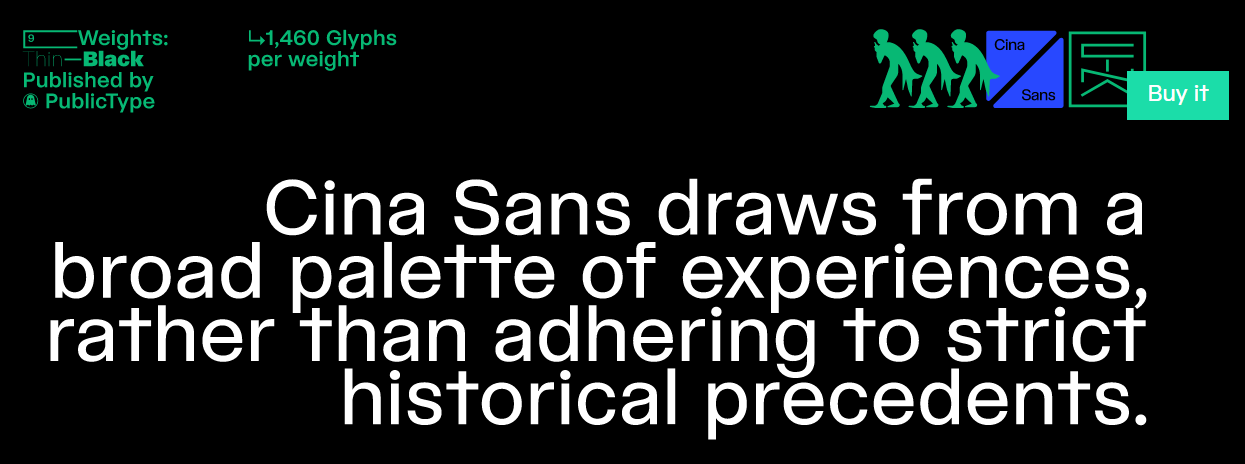
Cina Sans là kiểu chữ sans serif đậm cá tính, thuộc dòng Neo-Grotesque. Kiểu chữ này lấy cảm hứng từ Helvetica – một biểu tượng trong lịch sử thiết kế chữ nhưng được tái hiện qua nhiều lần cải tiến để tạo nên diện mạo mới, hiện đại và độc đáo hơn. Cina Sans là kết quả của sự nghiên cứu và tâm huyết của nhà thiết kế Andrés Torres, người luôn trăn trở với việc kế thừa và phát triển di sản lịch sử của các kiểu chữ kinh điển.
Bộ sưu tập Cina Sans bao gồm 9 độ đậm (weight), mỗi độ sở hữu 1.460 ký tự, mang đến sự đa dạng và linh hoạt vượt trội. Với thiết kế nhấn mạnh vào tính ứng dụng mà không hy sinh thẩm mỹ, Cina Sans không chỉ là một kiểu chữ mà còn là một công cụ thiết kế mạnh mẽ, giúp các nhà sáng tạo truyền tải thông điệp một cách hiệu quả và ấn tượng.
17. Font chữ: Vitamiin (Typokompanii)
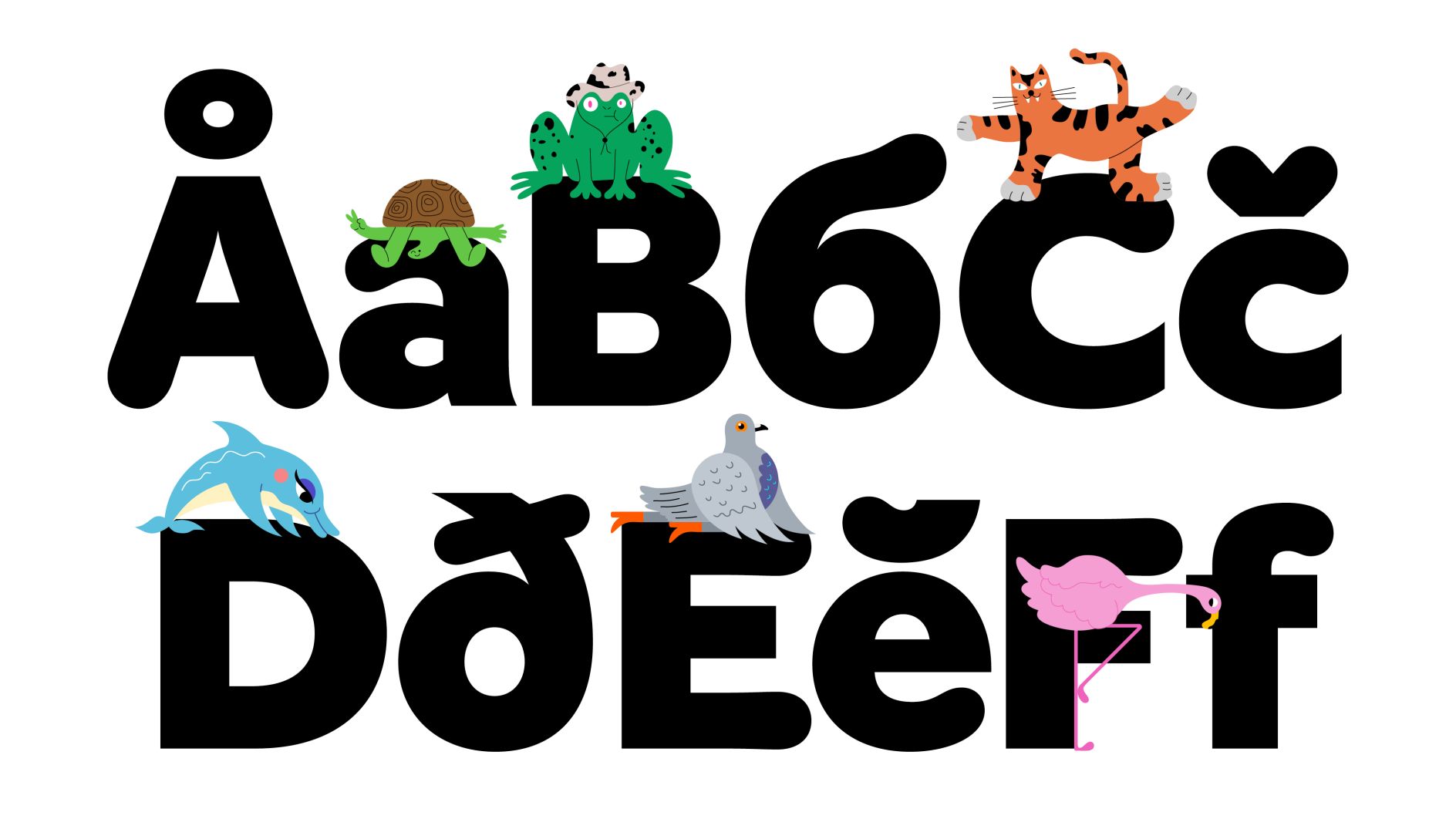
Vitamiin là kiểu chữ sans-serif mang phong cách vui tươi, thân thiện, nổi bật với các đầu nét tròn mềm mại, lý tưởng cho những thiết kế thương hiệu muốn tạo cảm giác thoải mái và gần gũi. Được các nhà thiết kế mô tả như một kiểu chữ “Semi-Softie”, Vitamiin khéo léo kết hợp giữa hai phong cách đối lập: Sự tự nhiên của Humanist và sự hiện đại, gọn gàng của kiểu chữ hình học. Điểm đặc biệt của kiểu chữ này nằm ở sự pha trộn độc đáo giữa các yếu tố tròn trịa và sắc nét, mang đến một thiết kế vừa cân đối vừa sáng tạo.
Bộ font Vitamiin hỗ trợ đầy đủ hệ chữ Latin và Cyrillic, mở rộng khả năng ứng dụng trên nhiều nền tảng và thị trường quốc tế. Đáng chú ý, các kiểu chữ nghiêng của Vitamiin được xây dựng bằng kỹ thuật xoay và nghiêng đầy sáng tạo, không chỉ tạo nên sự độc đáo mà còn mang lại tính thẩm mỹ cao. Với thiết kế linh hoạt và giàu sức sống, Vitamiin không chỉ phù hợp cho các dự án thương hiệu mà còn là lựa chọn lý tưởng cho các ứng dụng đồ họa hiện đại, nơi sự vui nhộn và ấn tượng trực quan được đặt lên hàng đầu.
18. Font chữ: Lato (Łukasz Dziedzic)
Lato là kiểu chữ sans serif cổ điển, nổi bật với vẻ ngoài thân thiện và là một trong những lựa chọn hàng đầu cho thiết kế web nhờ tính thẩm mỹ và khả năng ứng dụng linh hoạt. Được sáng tạo vào mùa hè năm 2010 bởi nhà thiết kế Łukasz Dziedzic tại Warsaw, cái tên “Lato” mang ý nghĩa “mùa hè” trong tiếng Ba Lan, thể hiện tinh thần tươi sáng và gần gũi của kiểu chữ này.
Kể từ khi ra mắt, Lato đã được phát hành dưới giấy phép mã nguồn mở Open Font License, cho phép cộng đồng thiết kế tự do sử dụng và tùy chỉnh. Với sự liên tục được cải tiến, phiên bản 2.0 mới nhất không chỉ nâng cao chất lượng mà còn dễ dàng được tích hợp trên nền tảng web thông qua Adobe Typekit, mang lại sự tiện lợi tối đa cho các nhà thiết kế. Sự kết hợp giữa nét cổ điển và tính hiện đại giúp Lato giữ vững vị trí là một công cụ đắc lực trong việc tạo ra các bố cục chữ trực quan, hiệu quả và thu hút.
19. Font chữ: Right Grotesque Mono (Pangram Pangram)
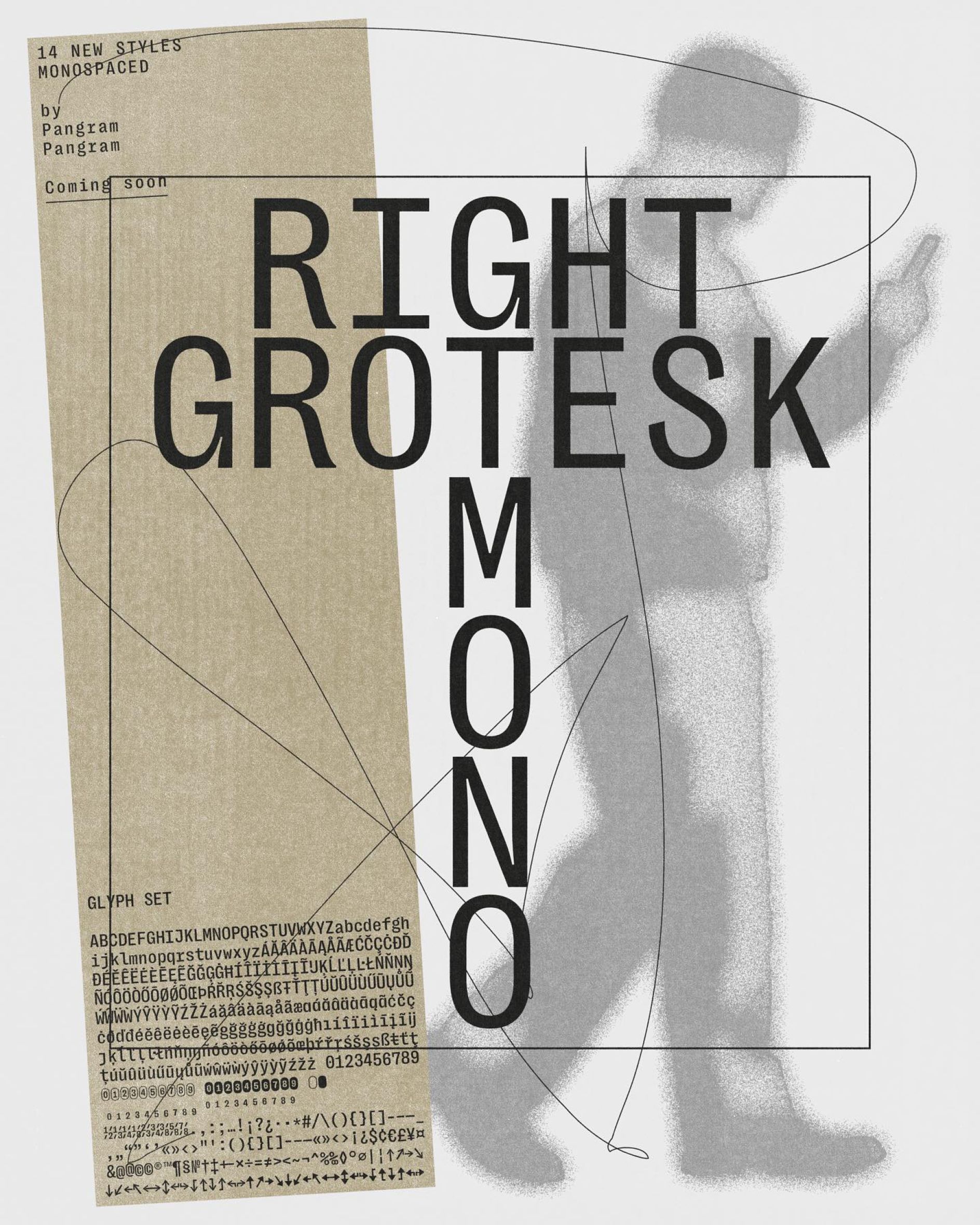
Right Grotesk là họ phông chữ sans serif được thiết kế với sự cân bằng hoàn hảo giữa tính đa năng và chất lượng cao, đáp ứng tốt cho cả những dự án nghiêm túc lẫn các thiết kế sáng tạo đầy màu sắc. Với các nét đều nhau mang phong cách hiện đại, kiểu chữ này kết hợp độ chính xác kỹ thuật sắc sảo cùng một phong thái độc đáo, tạo nên sự hài hòa giữa tính trung tính, chức năng và cá tính riêng biệt.